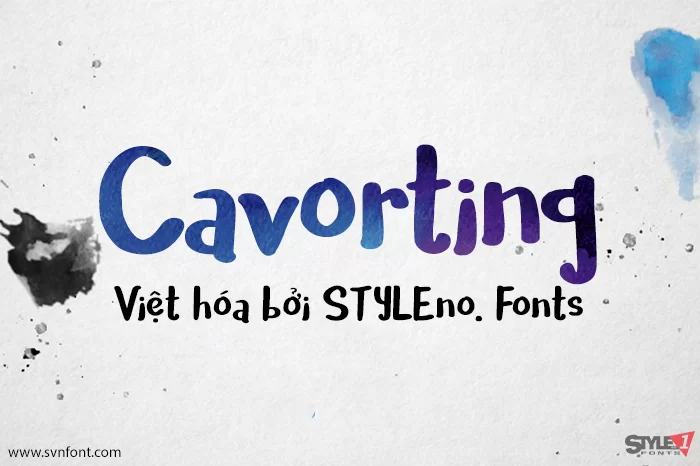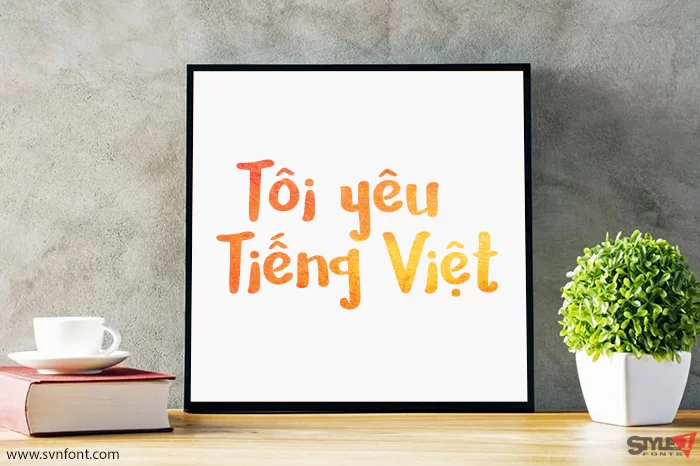
[Font Việt hóa] SVN-Cavorting một font chữ script rất đẹp dành cho typography
Cavorting là một phông chữ được tạo ra từ chữ viết tay thật. Phông chữ này rất hữu ích cho thiết kế poster, tiêu đề, áo phông và nhiều hơn nữa...
Nhà thiết kế: Missy Meyer
Việt hóa: STYLEno.1 Fonts